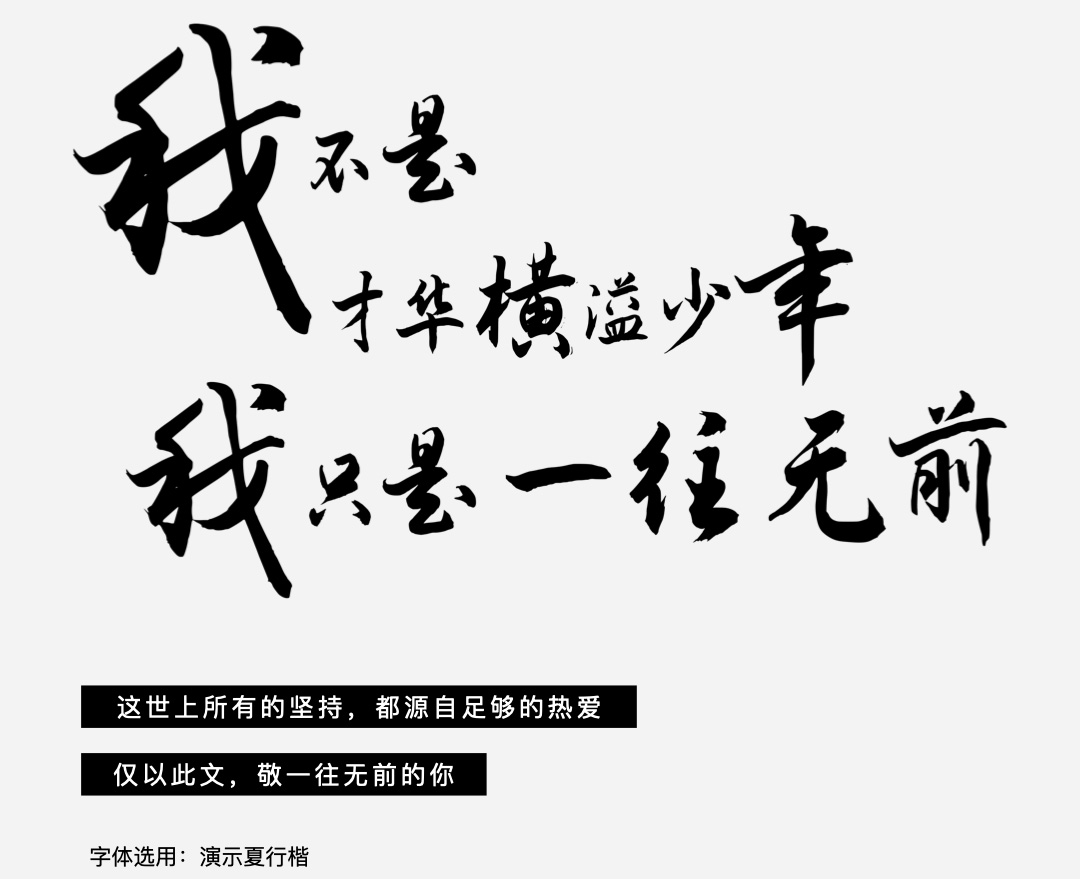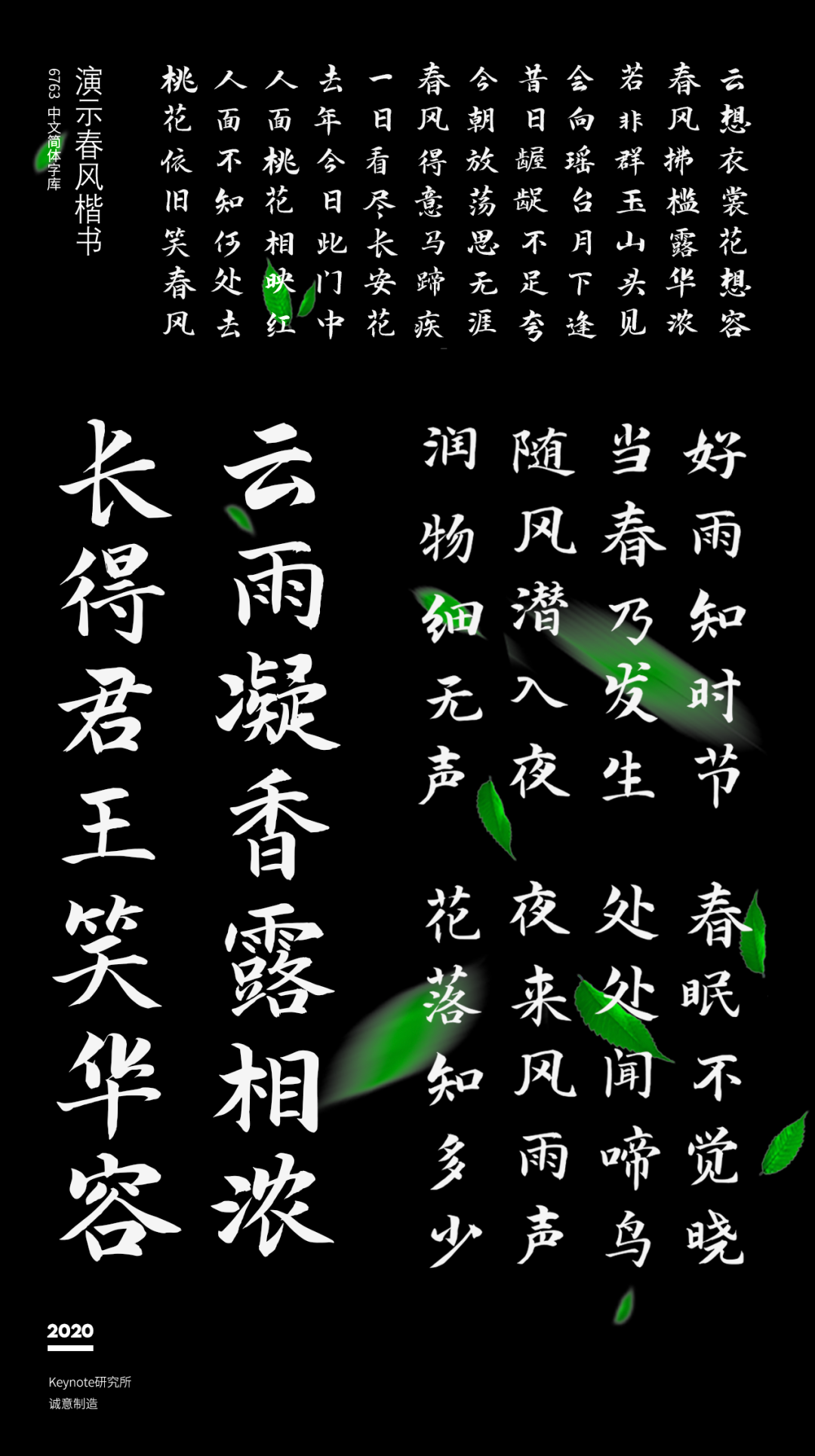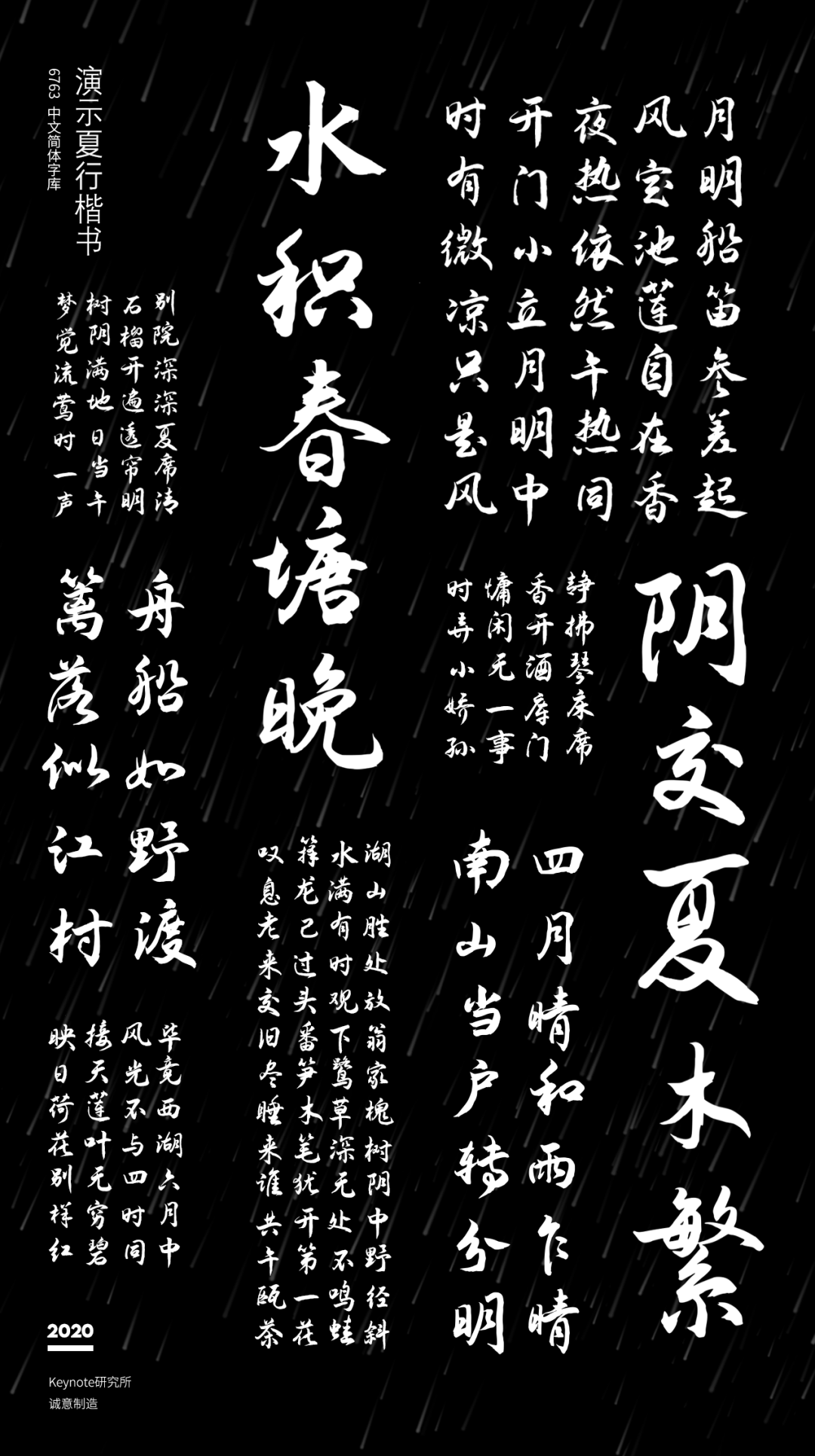
演示免费可商用字体“三连发” | 演示春风楷 | 演示夏行楷 | 演示秋鸿楷字体资讯
今天 keynote研究所人生哥将再次发布三款免费可商用字体,全部为半自动流程制作,当然已经做好了被某些人骂的准备,似乎一切手写字体都天生具备这种基因,所以,请让你们的狂风暴雨来的更猛烈一些吧!
这三款字分别为:演示春风楷演示夏行楷演示秋鸿楷
第一款:
演示春风楷
字稿作者:徐占海
1983年入伍,军人出身丨辽宁人丨每日笔耕不辍
字体制作:人生哥(和他的半自动电脑)
第2款:
演示夏行楷
字稿作者:刘锡栋
中国漓江书画艺术家协会理事丨北京中国书画研究院研究员丨中国民族硬笔书法家协会会员丨中国楹联学会会员丨黑龙江楹联家协会会员丨高级政工师,已退休
字体制作:人生哥(和他的半自动电脑)
第3款:
演示秋鸿楷
字稿作者:叶运鹏
高中教师丨辽宁人丨98年加入农民书画家协会
字体制作:人生哥(和他的半自动电脑)